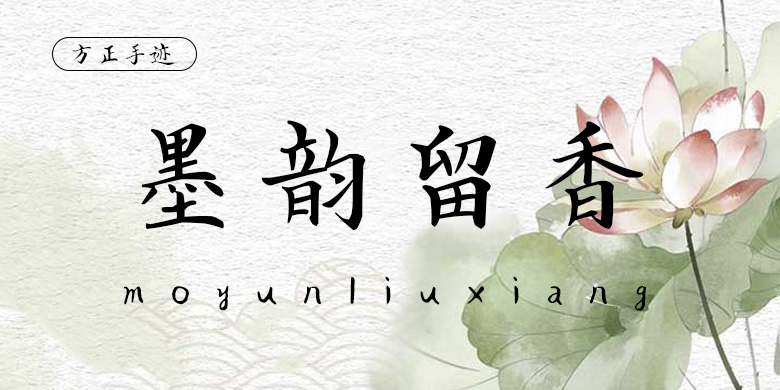
方正手迹-墨韵留香
字体品牌: 方正手迹 设计师:宋昱东 字体分类:常规书写·硬笔 字体属性:精品字 字符集:简繁扩展(GBK) 发布时间: 2020
墨韵留香是一款毛笔书写的楷书字体,字体取法高古直追汉简,多用侧锋用笔,转折处横轻竖重,对比强烈,力度感十足,整体大小错落,体现出书艺术中的矛盾之美,洒脱不羁而又不拘一格。适用于传统类的书刊、文化类品牌广告和产品包装设计,以及社交网络的个性化用字。